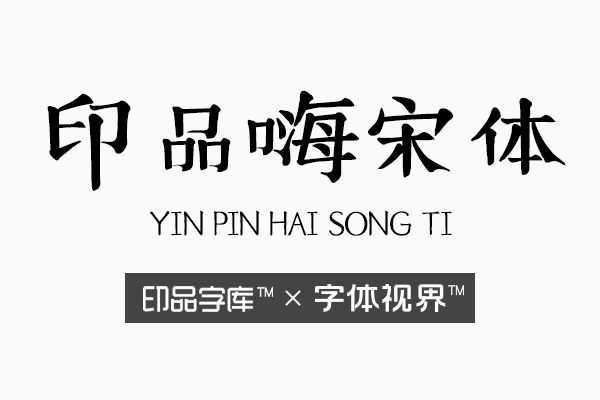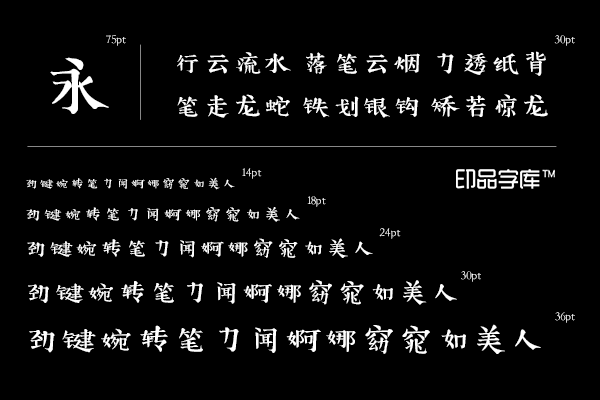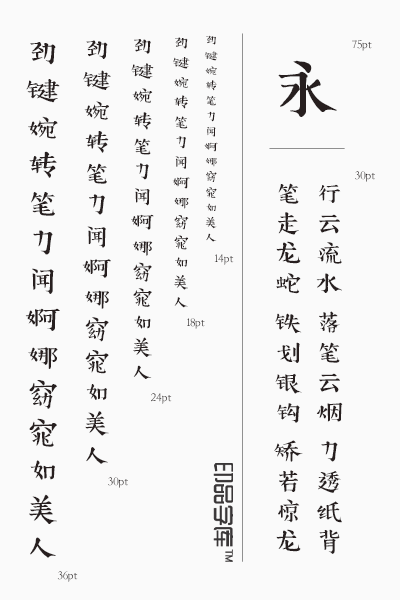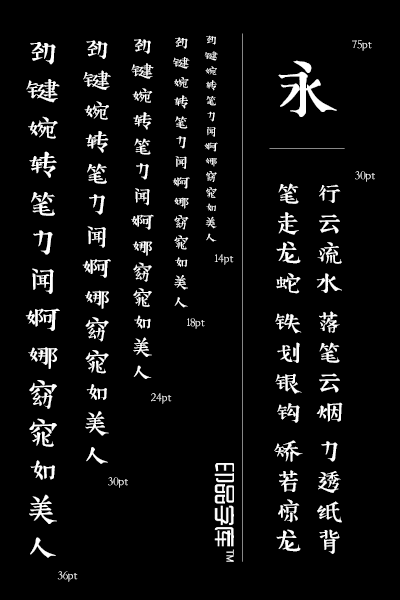
印品嗨宋字体又来了?它是谁?看名字也许你会猜是不是一个小品?还是一个相声?或是一个电视上的节目?不,这个印品嗨宋其实是字体设计中的一个艺术个性古灵字体哦。很意外吧。
那我们来看看这个印品字库的印品嗨宋是哪种作妖法?
字体的明显特征:其一精怪又古灵,其二不是凡品的气质字体,其三可爱可人。怎么样这些的描述放在一起是不是很难想象出这个组合会是哪种作妖状态?好吧我承认它的描述已经成功地将我好奇心勾引起来了。